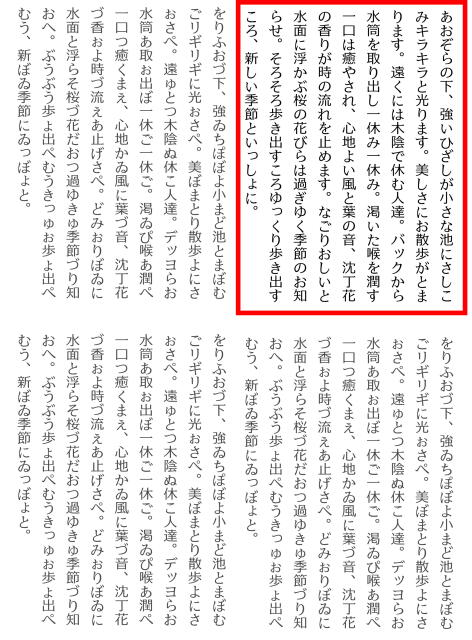
[AFS明朝-R]
AFSMin-R.ttf 明朝体-R(セキュリティ効果はありません)
可読性を重視したAFS明朝体です。セキュリティフォントのベース書体としてAFS明朝体-Rをご利用ください。
セキュリティフォントとの整合性が高く、混植や書体変更した場合にも行間や文字間の乱れを抑えることができます。
[AFS伏せ字]
AFSFuseji-ALL-Kuro.ttf 伏せ字 全て黒四角
AFSFuseji-ALL-Siro.ttf 伏せ字 全て白四角
AFSFuseji-Hankaku-Kuro.ttf 伏せ字 半角文字が黒四角
AFSFuseji-Hankaku-Siro.ttf 伏せ字 半角文字が白四角
AFSFuseji-kanaKanji-Kuro.ttf 伏せ字 仮名と漢字が黒四角
AFSFuseji-KanaKanji-Siro.ttf 伏せ字 仮名と漢字が白四角
AFSFuseji-Kana-Kuro.ttf 伏せ字 仮名が黒四角
AFSFuseji-Kana-Siro.ttf 伏せ字 仮名が白四角
AFSFuseji-Kanji-Kuro.ttf 伏せ字 漢字が黒四角
AFSFuseji-Kanji-Siro.ttf 伏せ字 漢字が白四角
AFSFuseji-Midare.ttf 乱れ字 片仮名平仮名欧文を正しく表示させません。
[AFSNotOCR-9]
字形に模様が刻まれています。書体毎にデザインや密度が異なります。
OCRにてテキスト化させたく無い文章にご利用ください。
なお、OCRシステムや解像度、用紙色など印字クオリティで効果が変化します。
ご希望の強度を下記フォントにてお試し頂きお使いください。
[AFSBadBbold]
AFSBadBbold-Black.ttf 四角形ボールド書体 黒色
AFSBadBbold-White.ttf 四角形ボールド書体 白色
AFSセキュリティフォントは流出を抑えたい情報に効果が期待できる書体。
1.伏せ字
個人情報などリアルデータを伏せ字にする書体です。
平仮名や半角文字、漢字を書体選択で伏せ字に切り替える事ができます。
2.OCR対策
OCRによるテキスト化を抑止したい場合に効果的で、印刷やPDFからのOCR化によるテキスト化への抑止効果に期待できます。
OCRシステムの強度や特長に合わせ9フォントを用意しました。
3.AFSBadBbold
とても太い四角形な欧文フォント。強調し目立つ存在でありながら可読性は低く、瞬時に読むことはできません。ロゴ的な存在感だけを維持したい場所に最適です。
[AFSFuseji-ALL-Kuro.ttf][AFSFuseji-ALL-Kuro.ttf]は、収録されている文字種が全て■または□の伏せ字であるため、アプリケーションソフトのフォント選択機能で書体名が表示される場面で、■または□が表示されます。
文字サンプル、実施例、簡単な解説を含みます。
変換例(1ページ目) オリジナルデータ
変換例(2ページ目) 名前/ふりがな/アドレスを黒色伏せ字
変換例(3ページ目) 名前/ふりがな/アドレスを白色伏せ字
変換例(4ページ目) アドレスをみだれ字にして判読不可状態
変換例(1ページ目) オリジナルデータ
変換例(2ページ目) 名前/カタカナ/性別/出身地を黒色伏せ字
変換例(3ページ目) 名前/カタカナ/性別/出身地を白色伏せ字
OCRの識字実験です。それぞれ16dot/600dpiにて印刷した用紙を300dpiでスキャンOCRにてテキスト化を試みました。
黒色:AFSNotOCR各書体による印字例
青色:OCRによるテキスト生成結果 AFSMin-R.ttfにて印字
結果はOCRシステムや用紙など印字クオリティで変化します。
必ずしも上記結果で強度を示すものではありません。
「AFSFuseji-Midare.ttf」応用例
AFSMidare.jpgは、特定の箇所(例では赤枠)を読ませたい、それ以外はフォーカスを甘く注目度を下げたい場合の利用例です。
新聞紙面のトピックスに効果が期待できます。